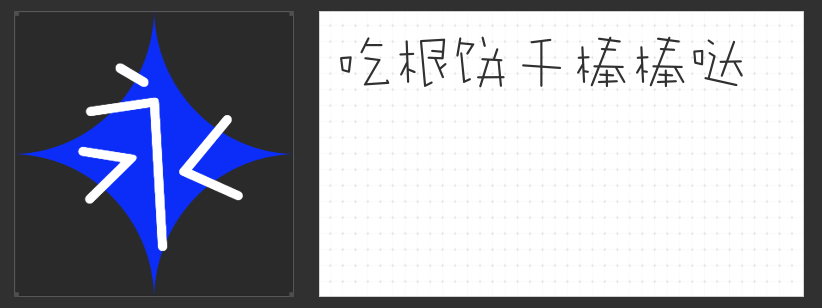
四款印刷设计专属字体:以形塑意,唤醒纸页的视觉呼吸
在印刷设计的语境中,字体不仅是信息的载体,更是构建视觉韵律的灵魂。从手写温度到几何秩序,从童趣天真到锋芒棱角,以下四款字体以独特的形态语言,为印刷品注入鲜活的生命力,让文字从平面中“生长”而出。
一、字恋狂风摇简 常规
这款字体以“失衡”为美学核心,笔画如被春风拂过的枝桠,带着自然摇曳的动态感。倾斜的横竖、夸张的撇捺,打破传统字形的稳定结构,却因手写般的拙朴感而显得温暖亲切。其比例的微妙失衡并非缺陷,反而营造出一种孩童涂鸦的天真,适合用于文艺书籍封面、诗歌集内页或独立杂志的标题设计,让文字在纸页上呼吸,传递不加修饰的真诚。
二、字恋狂饼干棒简 常规
以“饼干棒”为灵感,这款字体将汉字解构为圆润的几何模块。笔画分布自由如拼图游戏,部分结构甚至颠覆传统笔顺(如“圆”字的外框一笔画出),却因倒梯形的整体轮廓与开口细节,形成一种笨拙又可爱的视觉张力。其无拘无束的创意形态,适合儿童绘本、创意包装或年轻化品牌宣传册,用童趣打破印刷品的沉闷感。
三、励字钧线黑简 微黑
全直线设计赋予这款字体锐利的现代感,斜度与转折的精准控制,让每个字符如切割工整的金属片,既保持个性锋芒,又通过细节优化降低阅读疲劳。微黑的字重使其在印刷中既清晰可辨,又不显笨重,适合科技类书籍、企业年报或极简风格海报的标题与正文,用理性的几何语言诠释专业与高效。
四、励字综艺简繁
笔画加粗至近乎填满空间,却在拐弯处以圆润弧度软化刚硬感,形成“外方内圆”的视觉矛盾。横平竖直的骨架中暗藏微妙曲线,让字体在严谨中透出活泼气息。这种“粗而不拙”的设计,使其成为杂志标题、广告标语或品牌视觉系统的理想选择,既能吸引目光,又能保持印刷品的精致感。
从风摇的温柔到饼干棒的顽皮,从钧线的冷峻到综艺的灵动,这四款字体以形态为笔,在纸页上书写视觉的诗篇。它们不拘泥于传统,却以独特的逻辑重构文字之美,为印刷设计提供无限可能。